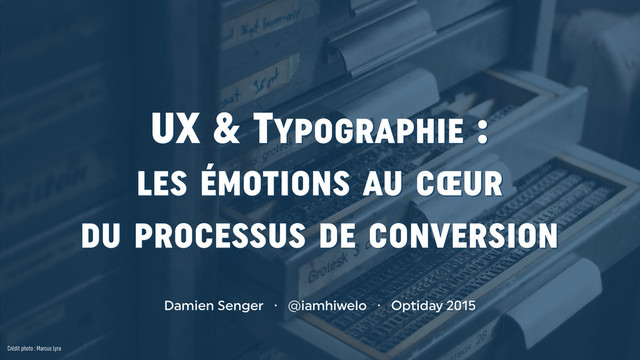
UX & Typographie : le design émotionnel au cœur...
UX & Typographie : le design émotionnel au cœur du processus de conversion
Conférence donnée dans le cadre de l'Optiday 2015, à Strasbourg, autour des problématiques d'optimisation marketing et de référencement des projets web.
1. UX & TYPOGRAPHIE : LES ÉMOTIONS AU CŒUR
DU
PROCESSUS DE CONVERSION Damien Senger · @iamhiwelo · Optiday 2015 Crédit photo : Marcus Lyra
3. Je suis passionné · taré · obsédé · obnubilé par
la typographie
(rayez la ou les mentions inutiles) Crédit photo : Kevin Hackert
4. Crédit photo : Martina Yach Une expérience émotionnelle dispose
d’une plus forte empreinte mnésique : elle s’ancre dans notre mémoire long-terme.
5. Crédit photo : Javier Morales L’émotion créée par un élément
est
principalement déterminé par sa personnalité
6. Crédit photo : Pedro Ribeiro Simões Depuis Gutenberg et sa
première bible, le choix typographique est important.
7. Crédit photo : Platteville EMS Il faut choisir ses caractères
de manière
cohérente pour éviter les dissonances cognitives
8. Crédit photo : Luke Dorny Plus un univers sera cohérent,
plus l’utilisateur sera en confiance.
On maximise donc le potentiel de transformation
9. Crédit photo : Christopher Doyle Cooper Black : De la
révolution industrielle aux vols low-cost
10. Crédit photo : Marcus Lyra Comme il existe des profils
d’utilisateurs, il existe des profils typographiques
11. Crédit photo : Taryn Une typographie peut être :
•
ludique ou sérieuse
• féminine ou masculine
• onéreuse ou bon marché
• moderne ou ancienne
12. Crédit photo : wsquared photography & creative Ne réinventons pas
la roue : notre inconscient typographie est forgé
de toutes les images vues depuis notre enfance
13. Crédit photo : Rach Augmenter la lisibilité,
c’est maximiser l’apport
d’information
tout en garantissant un confort de lecture
14. Crédit photo : Jens Schott Knudsen Améliorer la lisibilité pour
lutter
contre le phénomène de rebond
15. Crédit photo : DAVID MELCHOR DIAZ Améliorer la lisibilité pour
faciliter
l’entrée dans le tunnel de conversion
16. Crédit photo : Raul Lieberwirth L’œil ne lit pas de
manière linéaire, il faut lui faciliter la lecture
17. Crédit photo : Doug Il faut prendre exemple sur les
milieux
« extrême » générateurs de stress : aéroports, métro & gares
18. Crédit photo : Isriya Paireepairit Dans ces environnements,
deux
facteurs sont à prendre en compte : • besoin de lisibilité (forte distance)
• besoin de rapidité d’accès à l’information
19. Crédit photo : Metropolitan Transportation Authority of the State of
New York Réfléchir l’affichage
et la pertinence des données : définir des niveaux d’information
20. Crédit photo : Metropolitan Transportation Authority of the State of
New York Avec un univers cohérent
et des niveaux d’information pertinents :
améliorons le confort des utilisateurs
21. Crédit photo : Platteville EMS Pour éviter la dissonance cognitive
: la forme doit être cohérente avec le ton
22. Crédit photo : relux. Le langage, l’iconographie et la typographie
selon la position dans le tunnel de conversion (en toute nuance bien sûr)
23. Par exemple, en amont du tunnel de conversion :
•
actions à l’infinitif
• typographie linéale géométrique
On assure la neutralité de l’information (objectivité, non oppression)
24. Par exemple, au sein du tunnel de conversion :
•
verbes d’action conjugués
• typographie linéale grotesque
On instaure une proximité bienveillante
(accompagnement, humanisation)
25. Crédit photo : Metropolitan Transportation Authority of the State of
New York LE CHOIX TYPOGRAPHIQUE PAR L’EXEMPLE
26. Crédit photo : Pascal Subtil Quand New York renaît de
ses cendres : une typographie presque sur mesure
27. Crédit photo : Mark Iocchelli En résumé, la question typographique
est incontournable à chaque étape de nos projets.